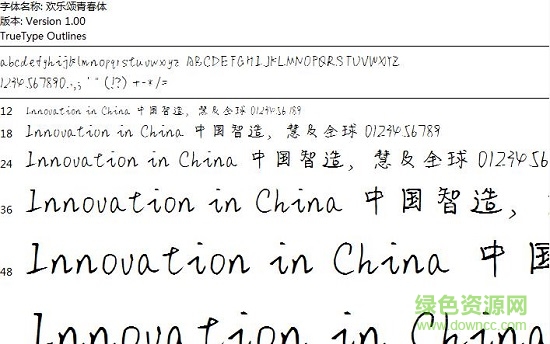
oppo歡樂頌青春體
歡樂頌青春體字體是一款充滿青春氣息的手寫字體,字跡連貫通暢,筆畫間的處理也十分的到位,有喜歡這款字體的朋友歡迎來綠色資源網(wǎng)下載!
歡樂頌青春體字體簡介
歡樂頌青春體是一款青春洋溢的手寫風格字體,這款字除了字跡娟秀好看之外,還非常的適合用來作為手機主題字體使用,在手機中會顯得格外的美觀!